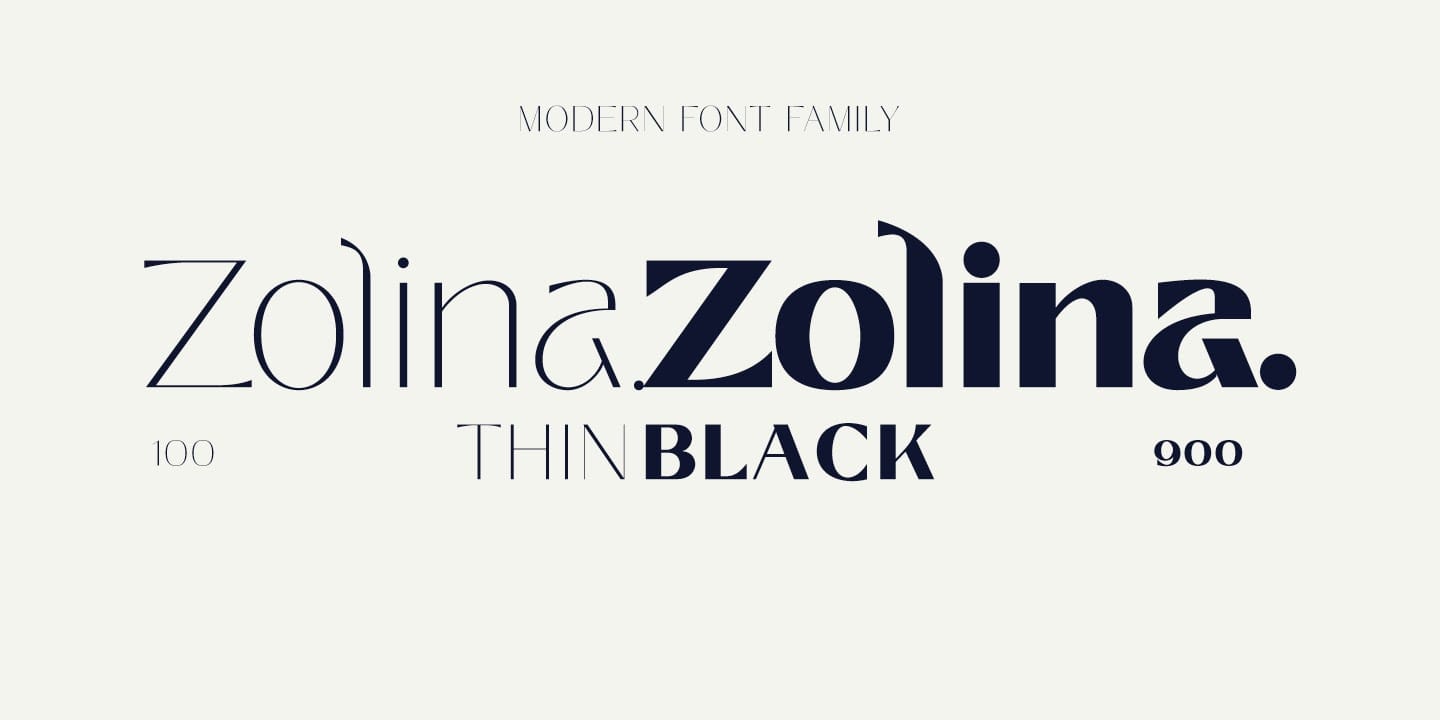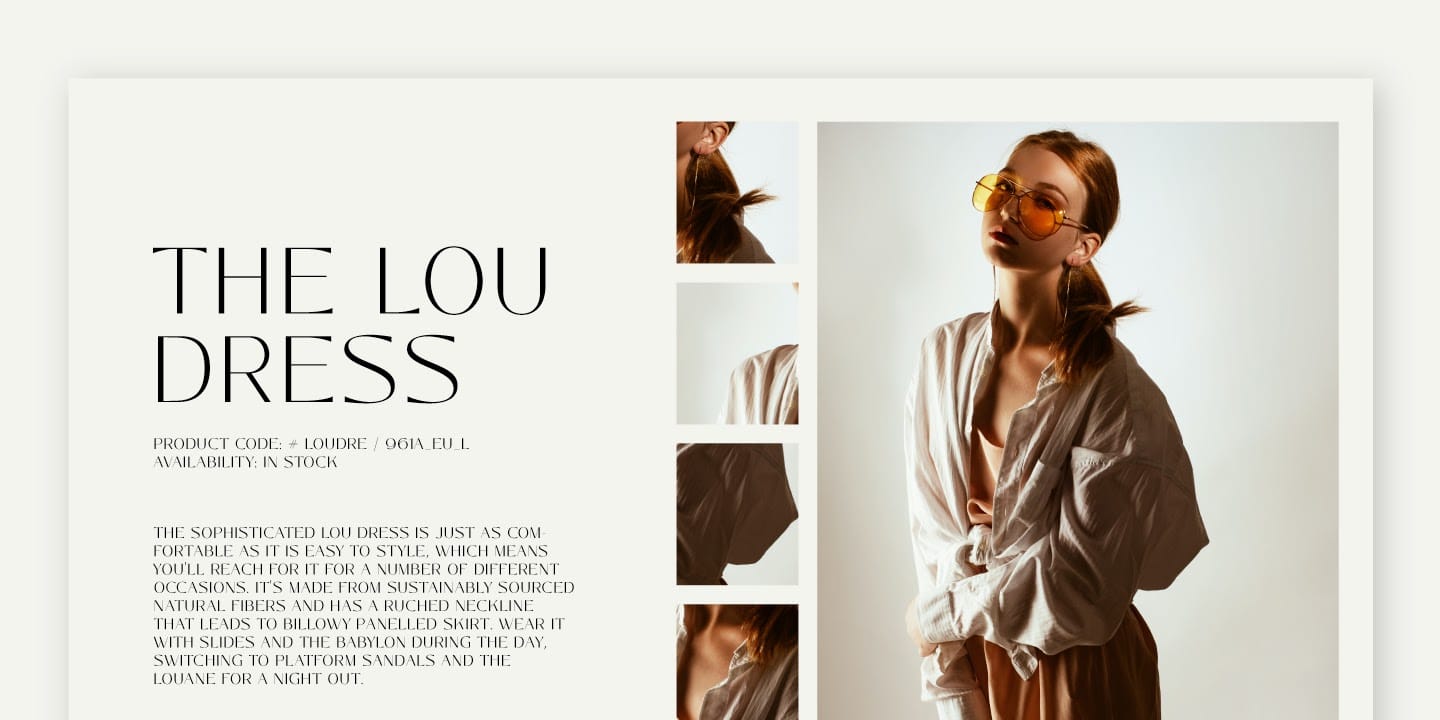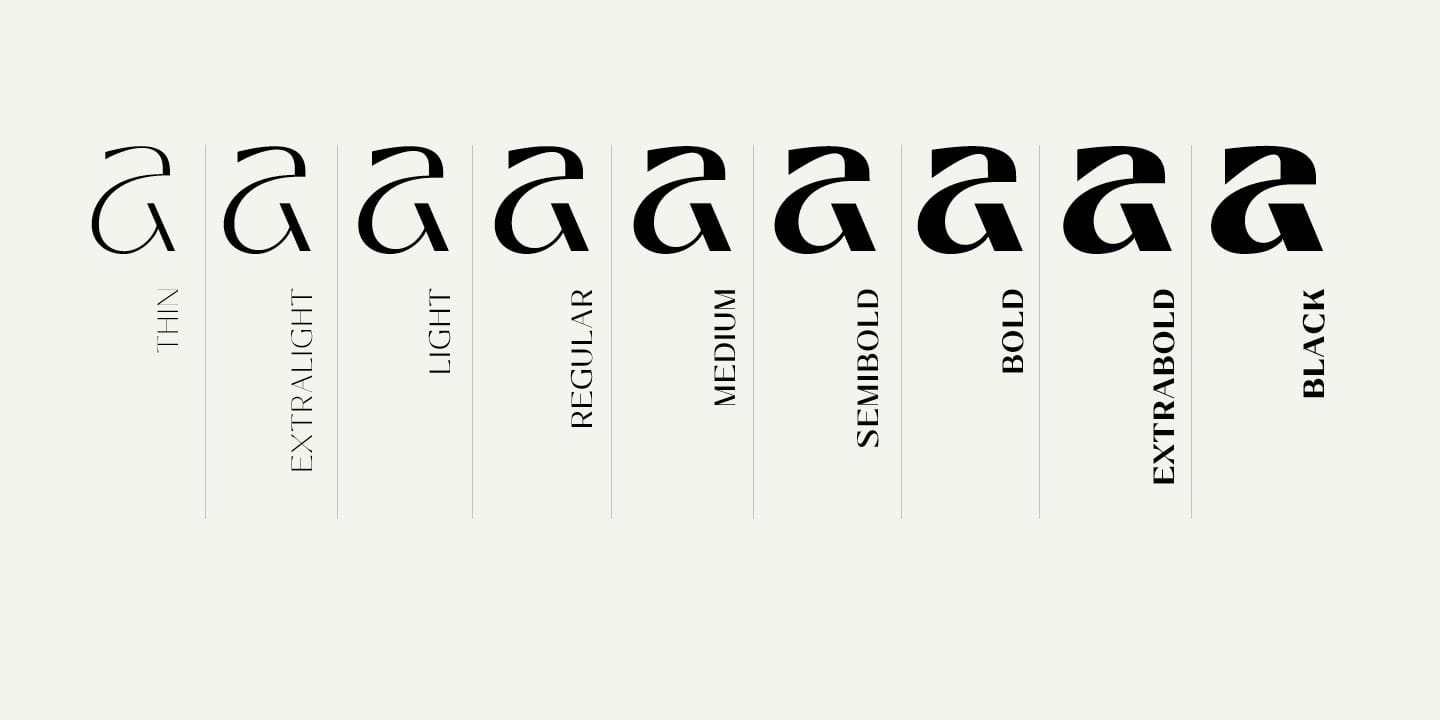
Font chữ độc đáo và thời trang, các đường thẳng kết hợp với một đường cong nhẹ tạo cho
Zolina vẻ ngoài hiện đại và xinh xắn. Hãy thử viết hoa để có cái nhìn thanh lịch và gọn gàng. Zolina hoàn hảo cho tiêu đề trang web, biểu trưng, story trên instagram hoặc thương hiệu liên quan đến thời trang. Font family này bao gồm 9 weight, variable style cũng như hỗ trợ đa ngôn ngữ.